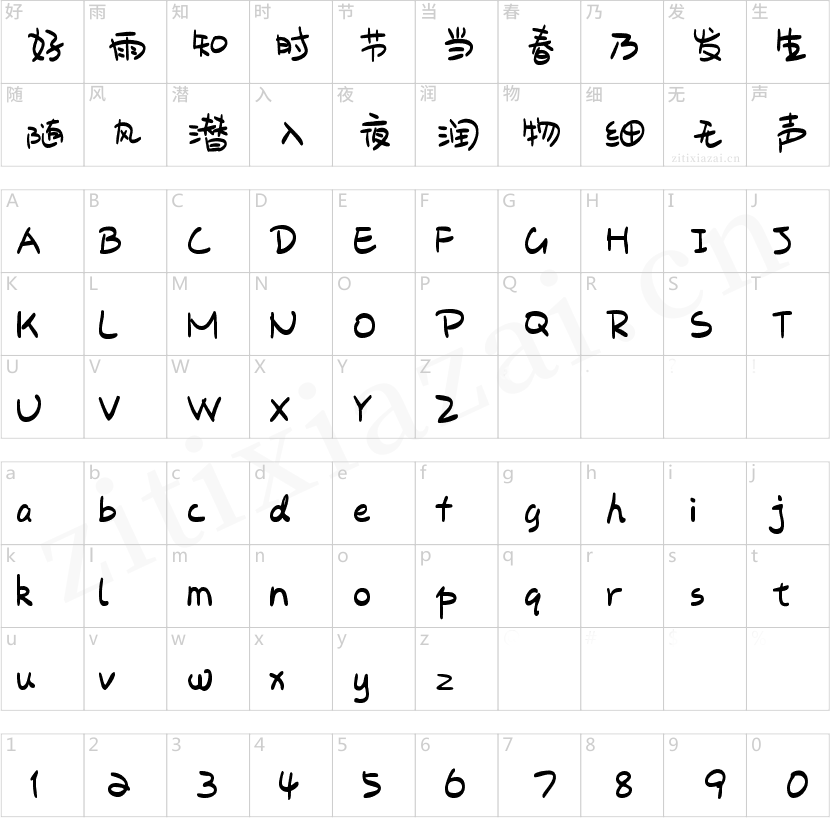
字魂79号-萌趣奶油体
字魂字体字小魂萌趣奶油体字体是由字魂创意字库设计并生产的一款可商用的字体,被收录于字小魂系列。该字体支持GB-2312标准,包含6764个中文、字母、符号和数字,字体类型偏向卡通可爱,具有活泼、动漫、可爱、简约、时尚、圆润的风格,在市面上广泛用于荣誉证书、游戏、金融服务等场景。